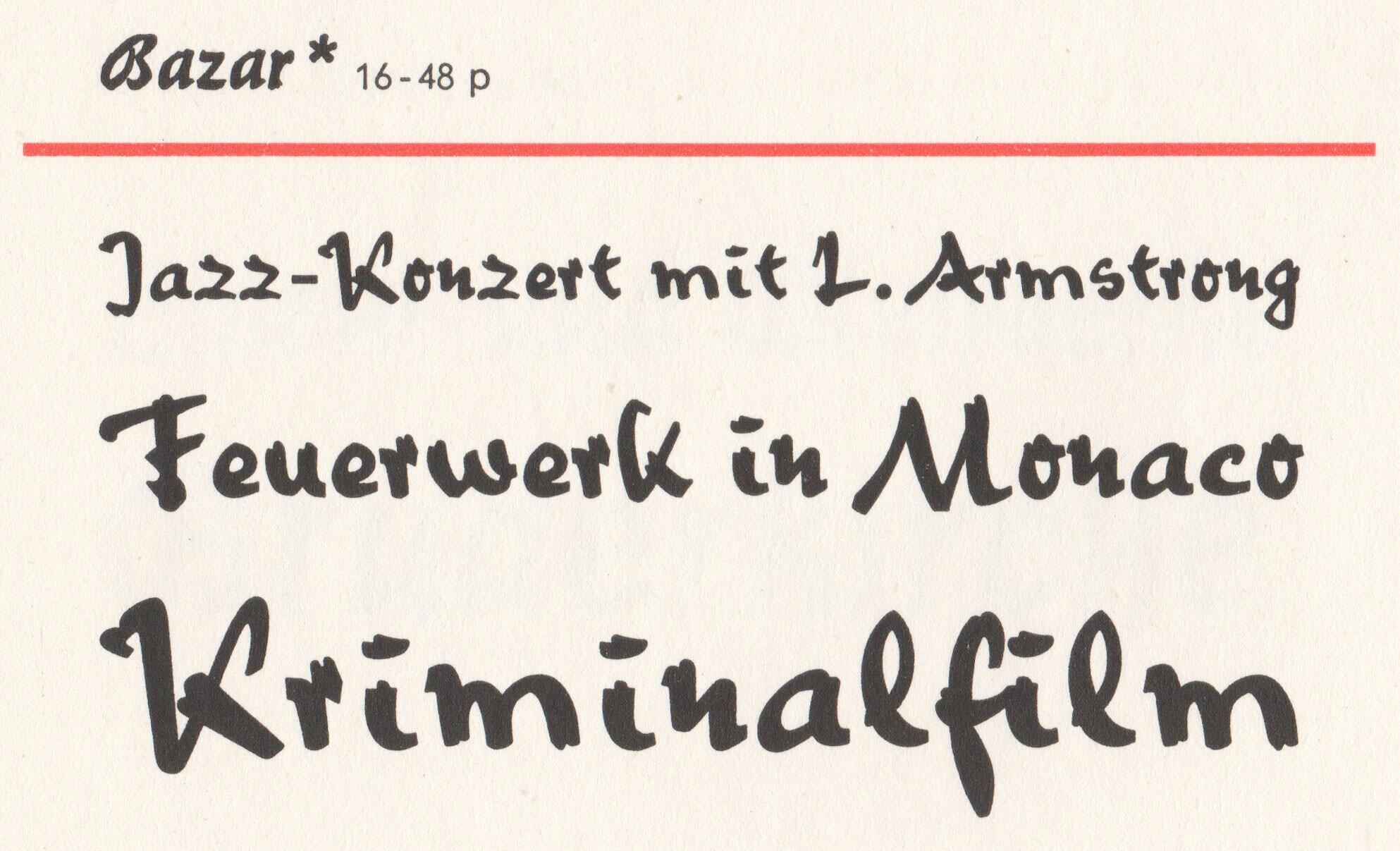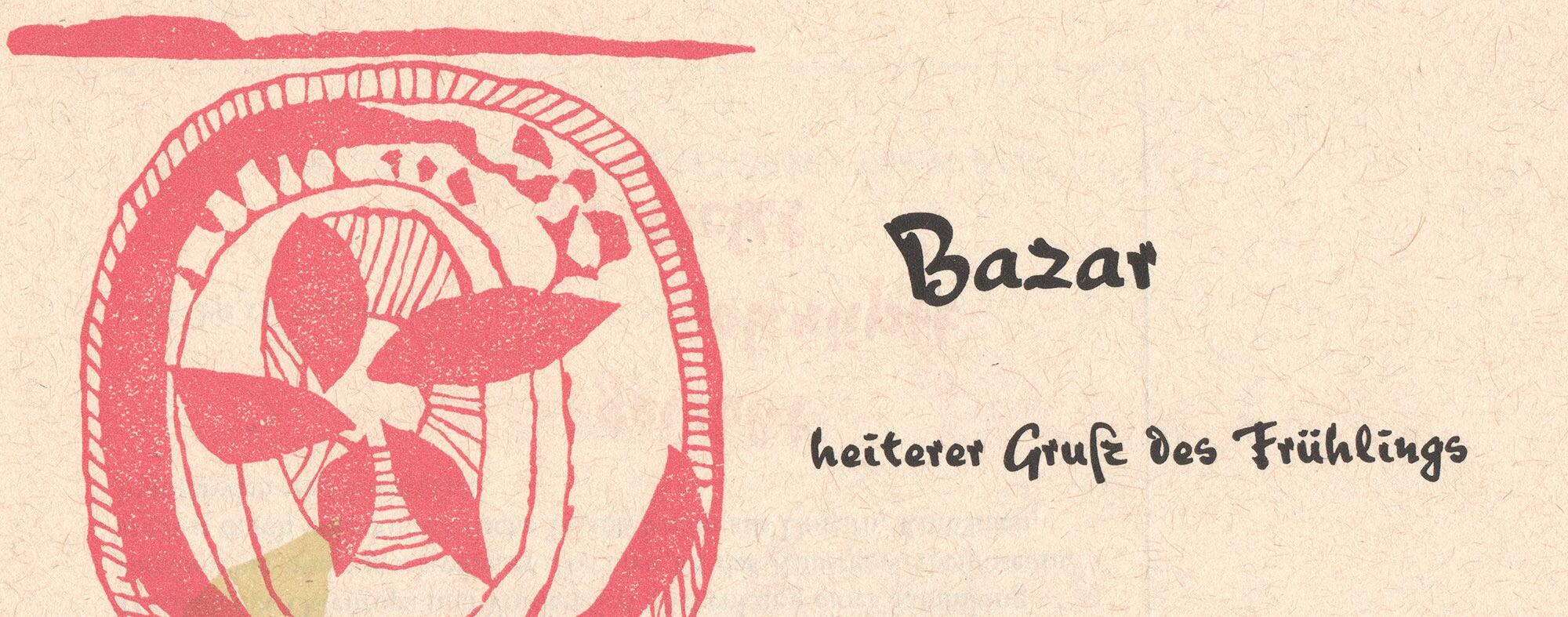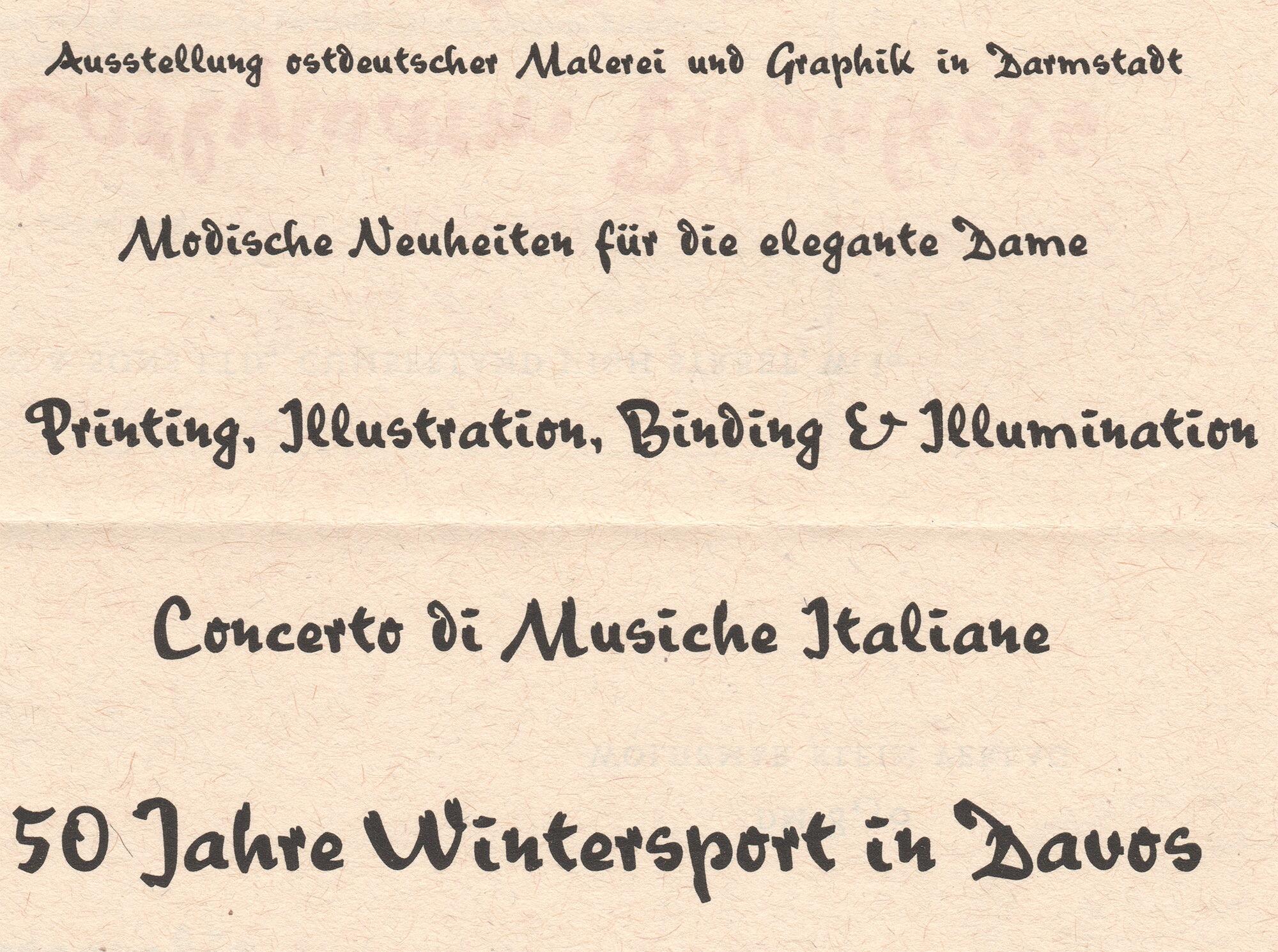
Die Bazar ist eine unverbundene Schreibschrift von Imre Reiner und erschien 1956 als Bleisatzschrift bei der D. Stempel AG.
Digitalisierungen gibt es als Bazar von Klaus Sutter (Linotype) und Boondock von Patrick Griffin (Canada Type).